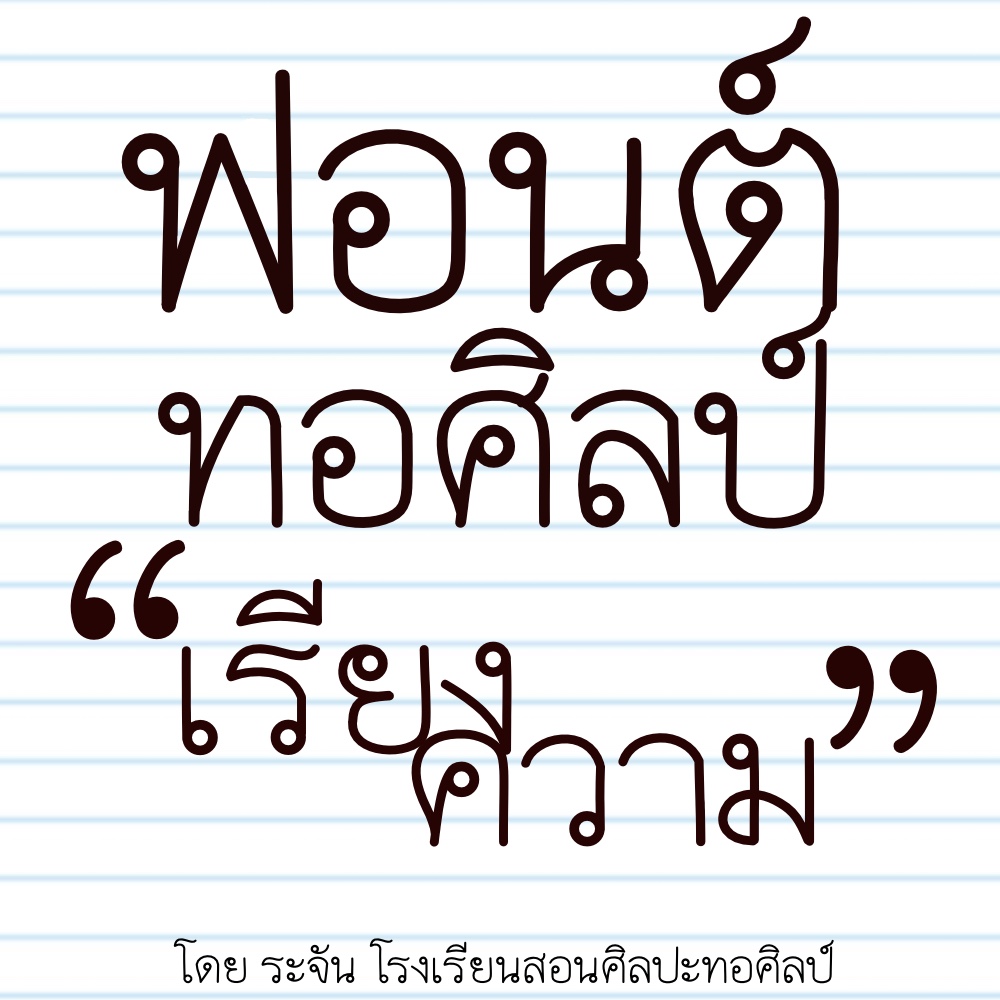
ทอศิลป์ เรียงความ
ตั้งแต่ทำฟอนต์ความฝันอย่างหนึ่งของตัวเองคือ มีฟอนต์พื้นเป็นของตัวเอง
แต่ฟอนต์ที่พื้นฐานที่สุด อ่านง่ายที่สุด กลับลงมือทำยากอย่างที่สุด
ไอเดียที่ใช้ในการออกแบบฟอนต์ตัวนี้คือ เวลาเห็นบทคัดเรียงความ
ของนักเรียนทั้งหลายแล้วรู้สึกว่า สุดยอดมาก เป็นตัวเขียนคัดลายมือ
ที่เหมือนตัวพิมพ์เลย ก็เลยอยากเอาทำเป็นฟอนต์ ให้รู้สึกเหมือนว่า
เป็นตัวพิมพ์ที่มีอารมณ์ตัวเขียนอยู่ด้วยในตัวฟอนต์
เลยได้ฟอนต์ชื่อ "ทอศิลป์ เรียงความ" สำเร็จออกมานี่แหละครับ